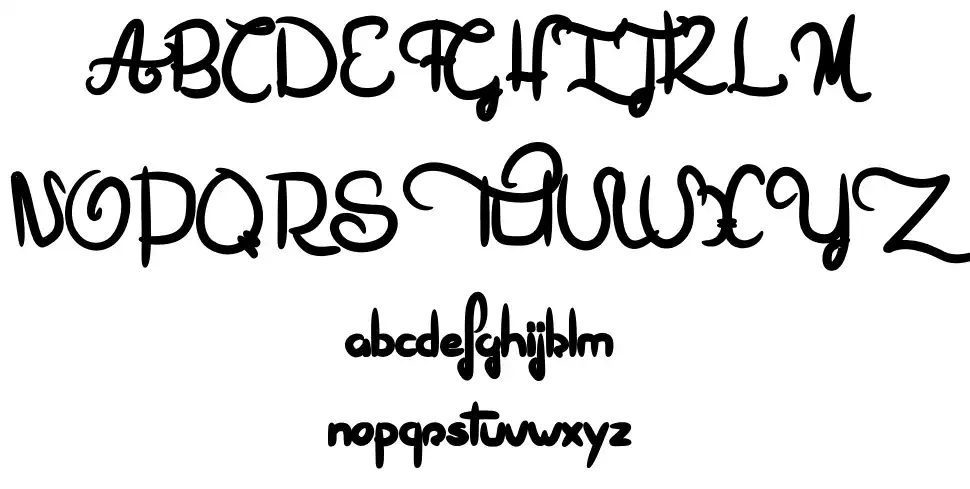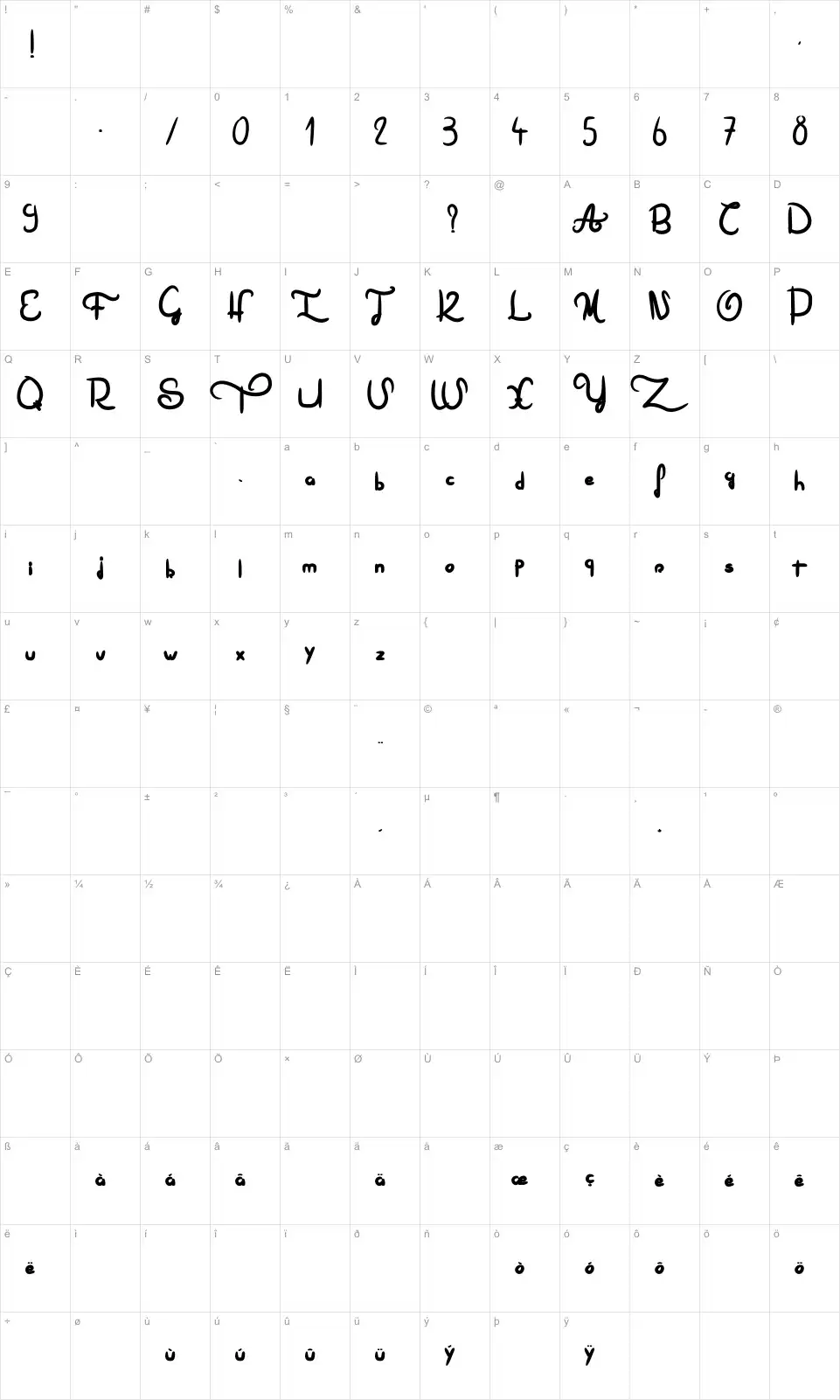
A fonte ‘This is not a font’, criada pelo designer Maelle.K, é uma opção de tipografia script versátil que está disponível para uso pessoal. Licenciada sob uma versão gratuita, esta fonte é disponibilizada em formato TTF e categorizada como script. Adicionada ao banco de fontes em 11 de julho de 2022, ela já acumulou 1599 downloads. Com um tamanho de arquivo de 695 KB, ela é adequada para uso em projetos de design de nível médio a avançado. Se você está procurando por uma fonte que ofereça versatilidade em diferentes projetos, essa é uma excelente opção. É possível baixar a fonte diretamente ou gerar uma pré-visualização personalizada de texto online para ter uma ideia de como ela se comportará antes de usá-la. Visite o site do designer, Maelle.K, em seu Facebook pessoal para mais informações e atualizações sobre a fonte e demais trabalhos.
Designer: Maelle.K